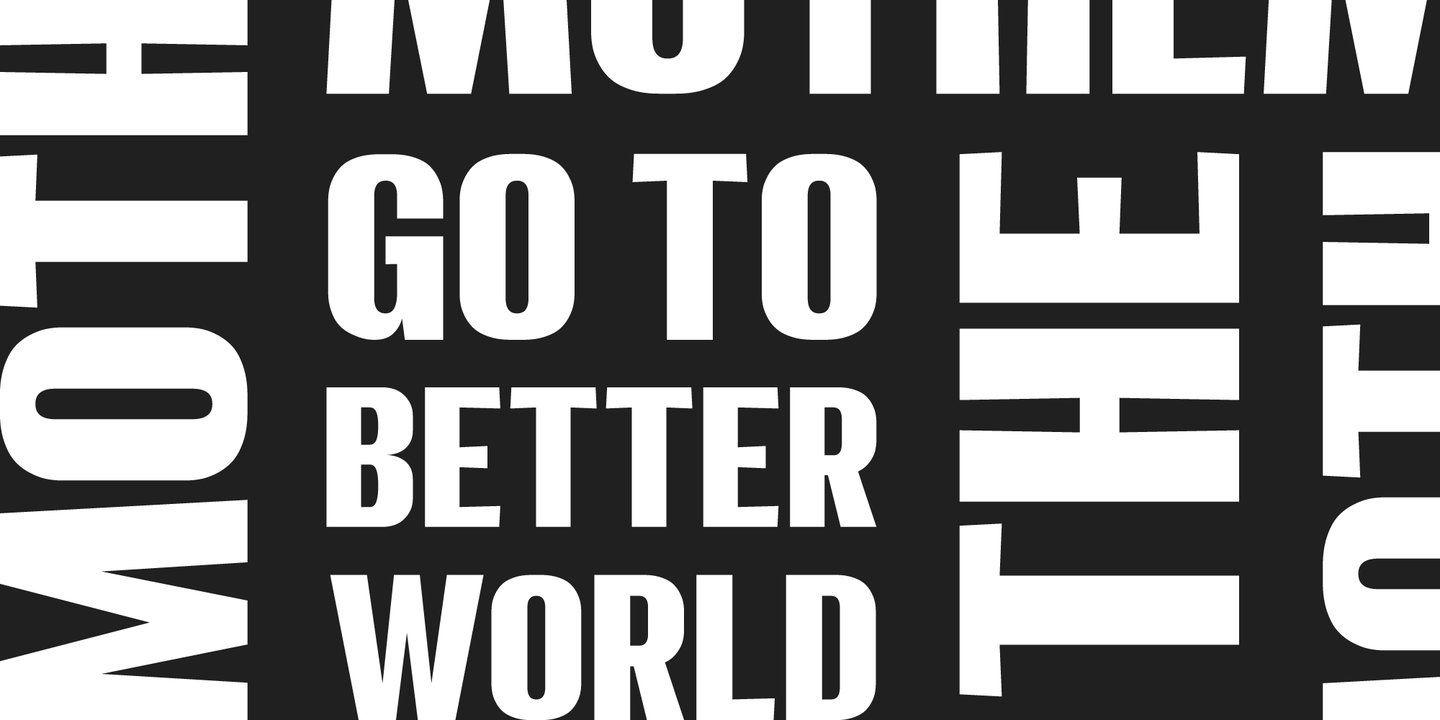
Mothem Font Family
Description de Mothem Font Family
Famille de polices MOTHEM avec trois modes, Black, ItalicBlack et ThinOutline et prise en charge par des fonctionnalités multilingues. La forme a une impression sportive, forte et futuriste, parfaite pour les designs élégants.